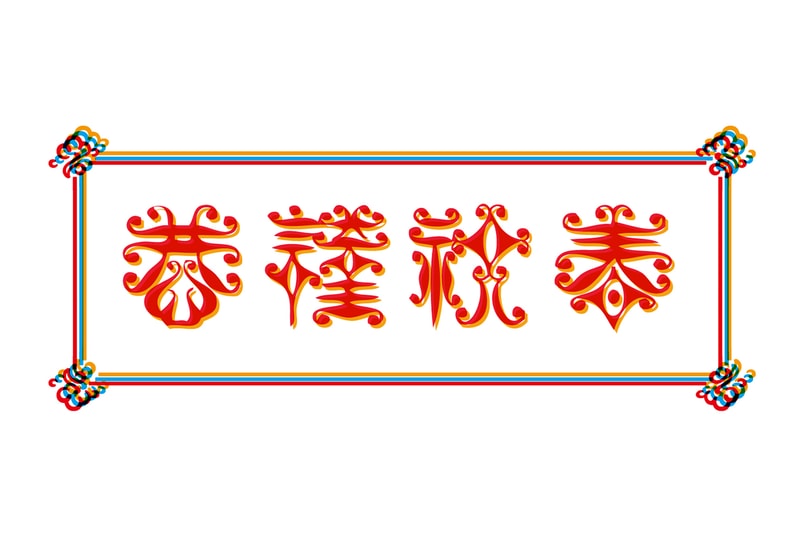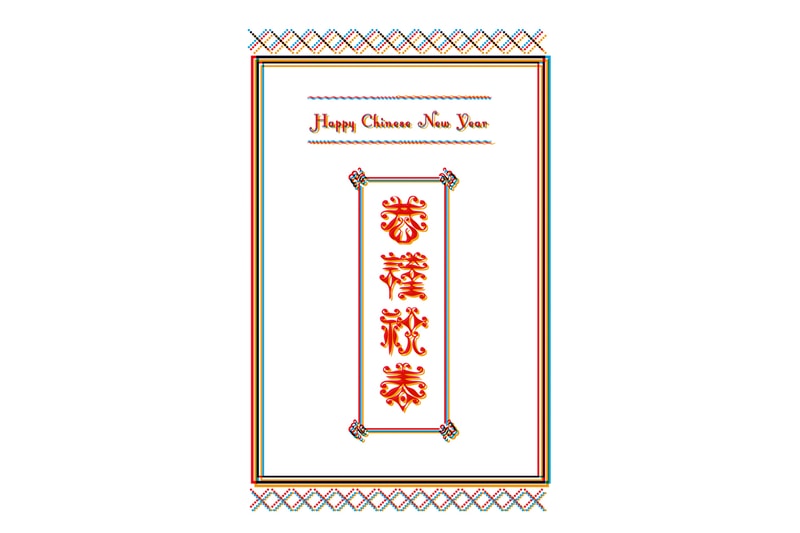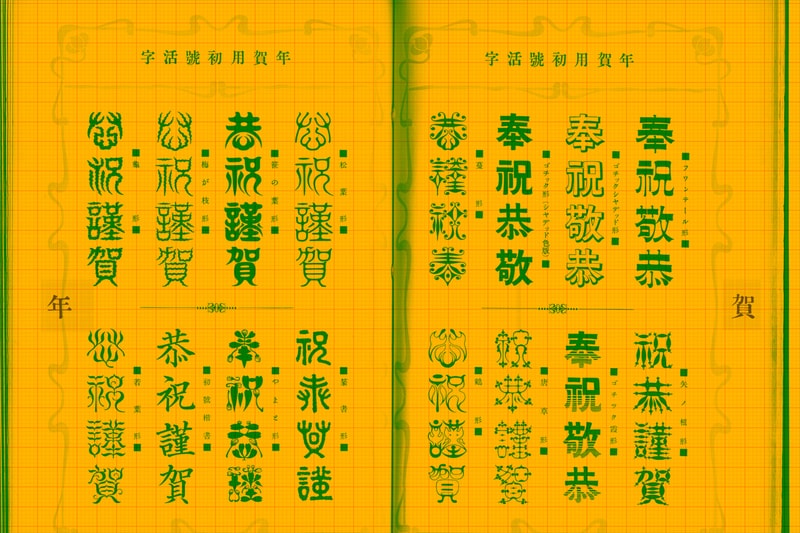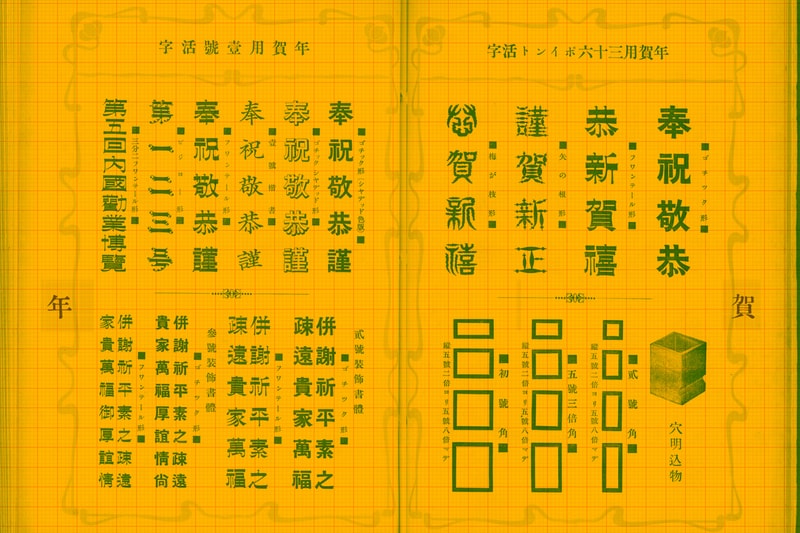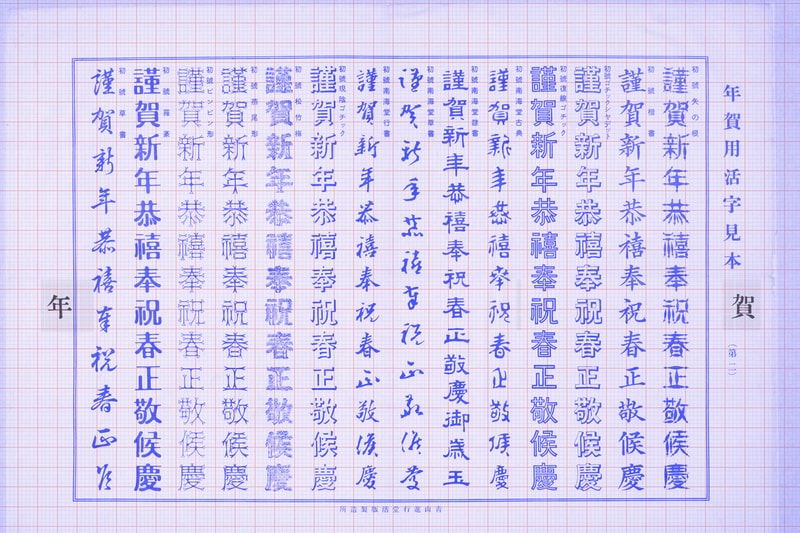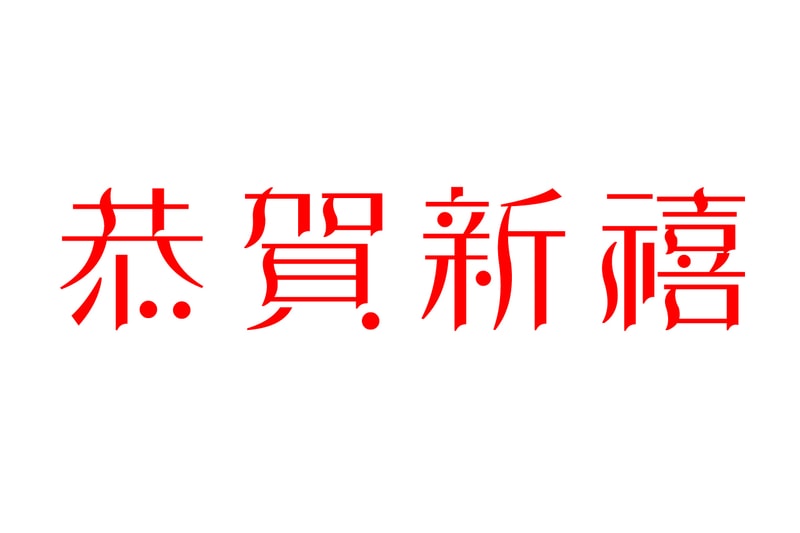
TYPOGRAPHY: 年贺文字
关于字型,别想得太复杂,笔者先借用一下某位字型设计师的穿衣譬喻法。这就像穿上 Amarni 的西装就是适合正式场合,穿上 The North Face 的外套就会想去户外,BAPE 的衣服就会感到一股年轻有活力的街头潮流,亦或是穿上了 Pendleton 总觉得好像也满符合过年的喜庆洋洋。当然,这些举的例子或许很诡异,但是应该很浅显易懂才是,毕竟这里是时尚生活流行网站嘛!然而,字型就是这么一回事,不管是西洋字体也好,中文字体也好,每个字体都各有各的氛围、机能、文化,端看你想诉求的是甚么。在什么场合我们都会很自然地去判断该穿什么样的衣服了,字型也是同样的道理。
今年二〇一三年的二月九日即是我们所谓的中国新年,为了应景,这次的主题也就先选定了「年贺文字」。对于现今各种非常制式了无生意的贺年卡是不是感到很厌烦了呢?这种十九世纪末至二十世纪初日本明治·大正时期(严格来说是从明治二〇年代末开始盛行)的装饰用字体是不是很美呢?竹叶型、藤蔓型、箭矢型、竹叶型、松叶型 ⋯⋯等等( ②、④)。而这些当时年贺广告用的装饰字体,即被日本当时称为「年贺文字」。
明治·大正时期历经了时代的动乱,也历经了文艺、绘画、音乐等全盛时期。我们常听到的「大正浪漫」, 便是这时期下的产物,成为当时的氛围、思潮、文化的代名词。而「浪漫」一词亦是从夏目漱石而来。而且明治·大正时期刚好涵盖了西方当时于十九世纪末盛行的 Japannism(日本主义,受到日本文化冲击而于西方流行的风格)、Art·Nouveau(新艺术运动,充满曲线曲面装饰的流行风格)、以及十九世纪初盛行的 Art·Deco(装饰艺术运动,充满几何线条的流行风格)⋯⋯等等。你看这些活字样本里的风格,是不是很容易联想到 Art·Nouveau 风格代表的法国地下铁入口 Metropolitain 呢? ⑤
在此也顺便推荐了一些有趣的怀旧字型给各位参考看看。由日本 idfont 所出的 怀游体⑥ 、怀欧体⑦ 、怀流体⑧ 、怀石体⑨,以及几款怀旧西洋字型 ⑴、⑵、⑶。日本 idfont 字型有免费试用版、付费正式版两种可以下载,只是免费试用版能使用的汉字相对的较少就是了。是不是很有明治·大正时期时的,Art·Nouveau 和 Art·Deco 的风格呢?虽然是日文字型,但是华文圈的使用者不必担心,只要先用中文输入法打出中文后,再套上想要的字型种类一样可以使用。